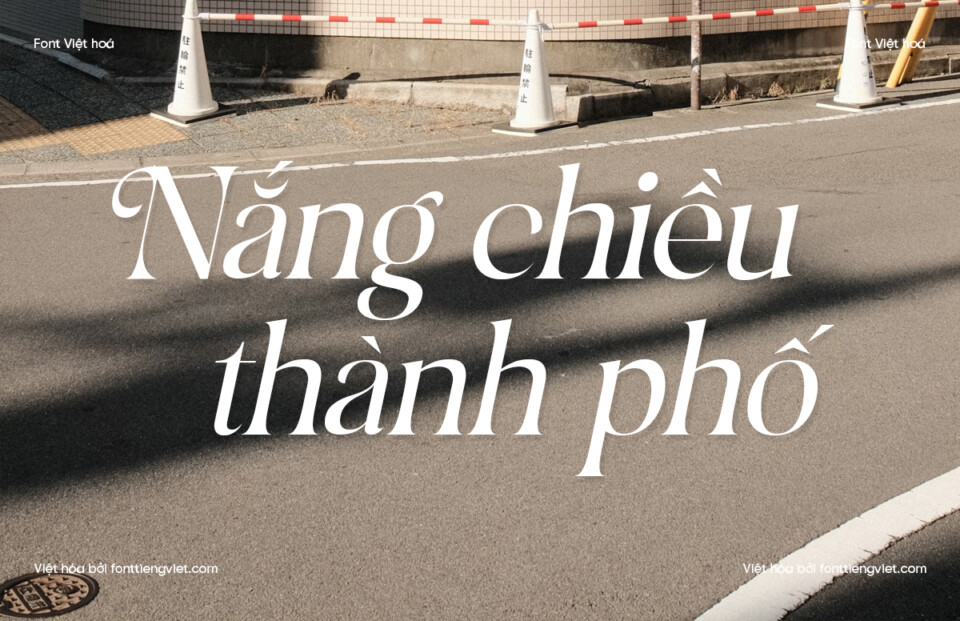
Font Việt hóa 1FTV VIP Qalogre Italic
Giới thiệu về Font Việt hóa 1FTV VIP Qalogre Italic
Trong thế giới thiết kế đồ họa hiện đại, việc lựa chọn một bộ Font Miễn Phí chất lượng luôn là ưu tiên hàng đầu của các designer chuyên nghiệp và nghiệp dư. Đặc biệt, Font Việt hóa 1FTV VIP Qalogre Italic nổi lên như một hiện tượng nhờ sự kết hợp hoàn hảo giữa nét cổ điển và hơi thở đương đại. Đây là một bộ font chữ thuộc dòng Serif cách điệu, mang trong mình những đường cong mềm mại nhưng vẫn giữ được cấu trúc vững chãi. Với kiểu dáng nghiêng đặc trưng, font chữ này tạo ra cảm giác chuyển động tinh tế, giúp các bản thiết kế trở nên sống động và có hồn hơn bao giờ hết. Việc sử dụng phiên bản Việt hóa giúp người dùng tại Việt Nam hoàn toàn yên tâm về khả năng hiển thị tiếng Việt chính xác, không bị lỗi dấu hay sai lệch khoảng cách ký tự.
Đặc điểm nổi bật của Font Việt hóa 1FTV VIP Qalogre Italic
Thiết kế Serif Italic độc đáo
Font Việt hóa 1FTV VIP Qalogre Italic gây ấn tượng mạnh mẽ bởi các chân chữ (serif) được gọt giũa tỉ mỉ. Kiểu chữ nghiêng không chỉ mang lại vẻ thanh lịch mà còn thể hiện sự sang trọng, đẳng cấp thường thấy trong các tạp chí thời trang hoặc nhãn hàng cao cấp. Mỗi chữ cái đều được chăm chút để đảm bảo tính thẩm mỹ cao nhất, tạo nên một tổng thể hài hòa và chuyên nghiệp cho mọi layout từ đơn giản đến phức tạp.
Khả năng ứng dụng đa dạng trong thiết kế
Nhờ vẻ ngoài tinh tế, bộ font này cực kỳ phù hợp cho các dự án thiết kế logo, tiêu đề bìa sách, thiệp mời đám cưới hoặc các ấn phẩm quảng cáo mỹ phẩm. Font Việt hóa 1FTV VIP Qalogre Italic giúp truyền tải thông điệp một cách nhẹ nhàng nhưng đầy sức thuyết phục. Ngoài ra, các bạn học sinh và sinh viên cũng có thể sử dụng font này để trang trí slide thuyết trình hoặc làm bài tập sáng tạo, giúp bài làm trở nên nổi bật và thu hút sự chú ý của thầy cô và bạn bè.
Tối ưu hóa tiếng Việt hoàn chỉnh
Một trong những điểm mạnh lớn nhất của phiên bản 1FTV chính là bộ dấu tiếng Việt được thiết kế chuẩn chỉnh. Các dấu thanh như huyền, sắc, hỏi, ngã, nặng được đặt ở vị trí hợp lý, đảm bảo không bị đè lên các ký tự chính hay làm mất đi vẻ đẹp vốn có của bộ font. Điều này giúp Font Việt hóa 1FTV VIP Qalogre Italic trở thành sự lựa chọn tin cậy cho những ai đang tìm kiếm sự hoàn hảo trong từng chi tiết nhỏ nhất của văn bản tiếng Việt.
Lưu ý khi sử dụng Font Việt hóa 1FTV VIP Qalogre Italic
Mặc dù đây là một bộ font tuyệt đẹp, người dùng nên lưu ý kết hợp nó với các font chữ không chân (Sans Serif) đơn giản để tạo ra sự cân bằng cho thị giác. Tránh sử dụng quá nhiều chữ nghiêng trong các đoạn văn bản dài để không làm mỏi mắt người đọc. Hãy để Font Việt hóa 1FTV VIP Qalogre Italic tỏa sáng ở những vị trí quan trọng nhất như tiêu đề chính hoặc các câu trích dẫn ngắn gọn để tối ưu hóa hiệu quả thẩm mỹ.